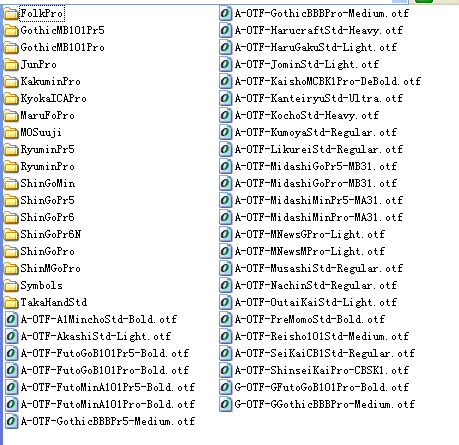
標(biāo)準(zhǔn)常用的日文字體是
MS Pゴシック和MS 明朝 (ms gothic & MS Mincho)
一般DTP印刷制品的最常用的字體是「新ゴシック體」shinGo
但是字體非常美觀,日本的地鐵站站牌看板都是用這個(gè)字體的,可見(jiàn)其普遍性
早就知道日文的字體,同樣的字體有帶P和不帶P的區(qū)別。比如"MS 明朝"和"MSP 明朝"。
但是一直不知道他們的區(qū)別,直到最近。
有P的是プロポーショナルフォント(Proportinal Font)-變幅字體
沒(méi)有P的是等(固定)幅フォント(Typewriter Font)-等幅字體
變幅字體字體幅度有大有小,自動(dòng)調(diào)整每行字的個(gè)數(shù)。
等幅字體字體固定大小,即使有標(biāo)點(diǎn)符號(hào)也不會(huì)改變每行字(標(biāo)點(diǎn)符號(hào))的個(gè)數(shù)。在文章中夾雜程序的時(shí)候,把程序的字體設(shè)成等幅字體,可以讓程序?qū)R,看起來(lái)更容易一些。